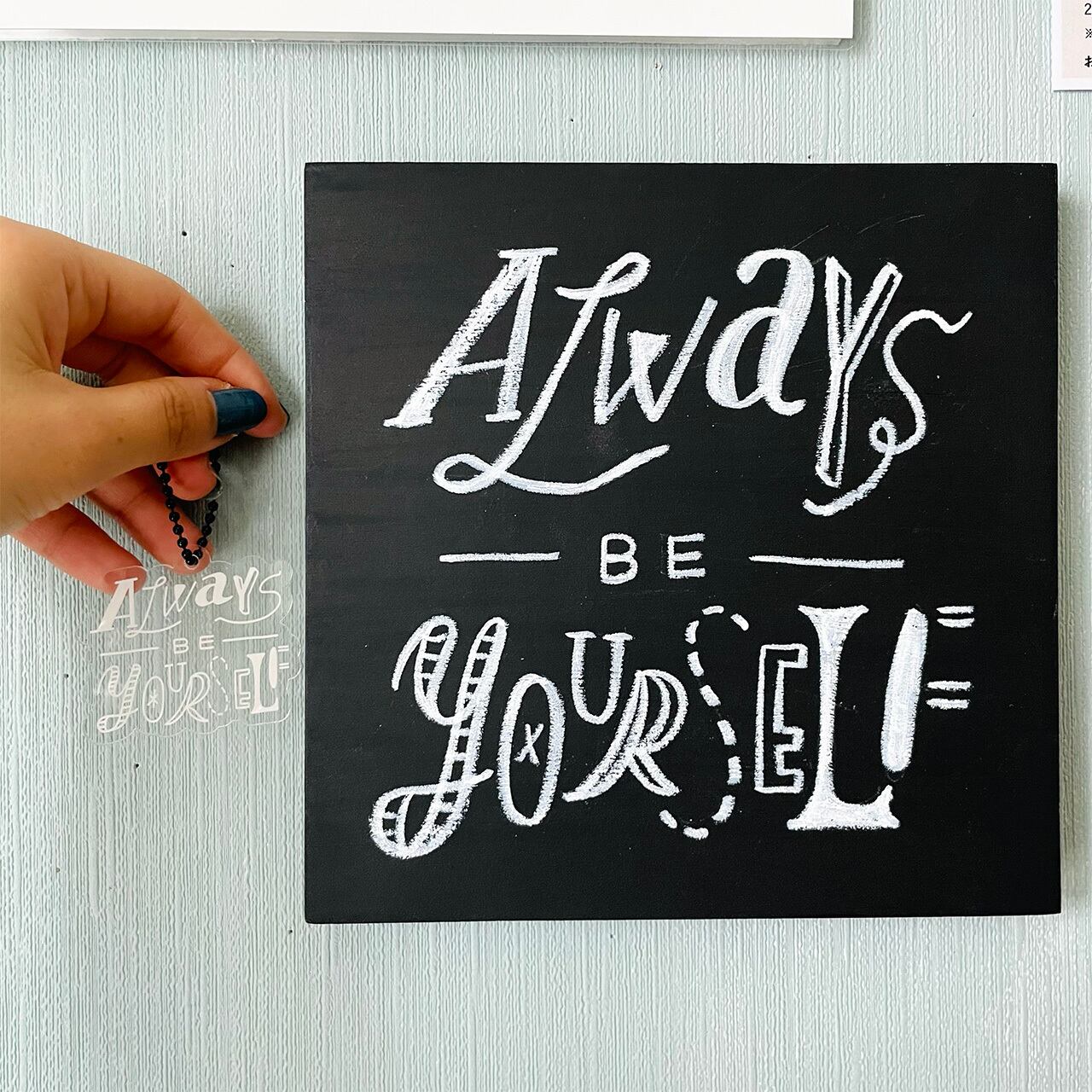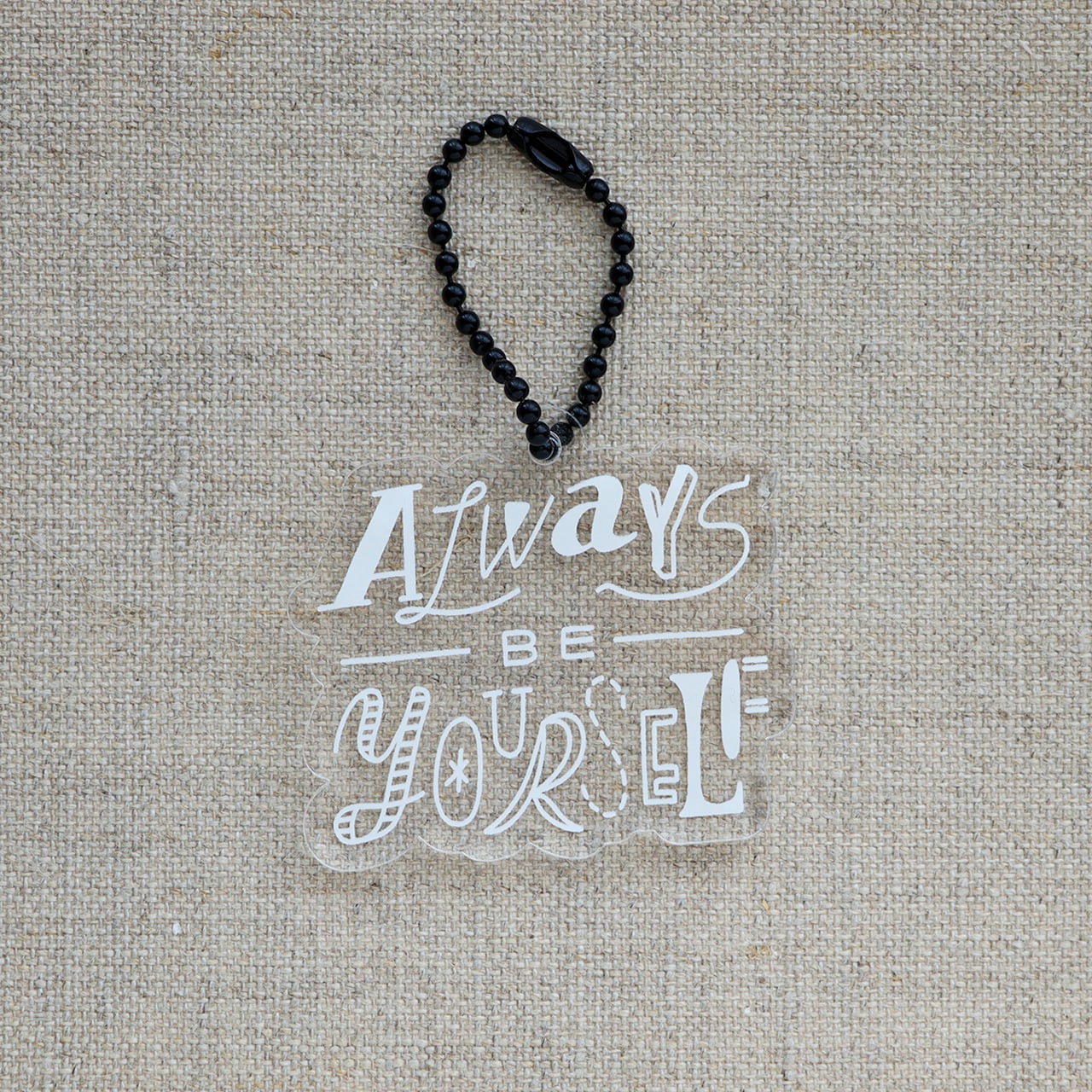
アクリルキーホルダー/Always be yourself.
ポジティブになれる言葉のキーホルダー作りました!
Always be yourself.
いつもあなたらしくありなさい
WSで選ばれる率No.1!なワード。
いろんなフォントをホワイトでシンプル仕上げました。
ブラックのチェーンがアクセント。